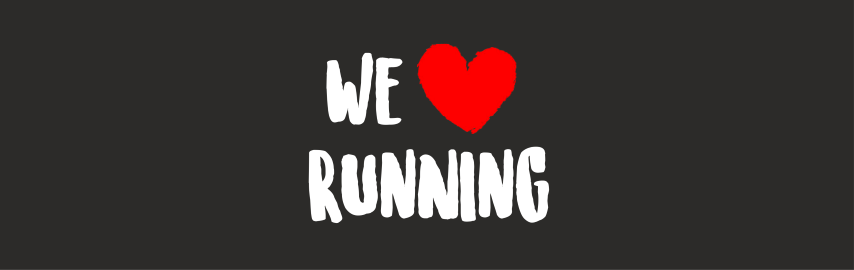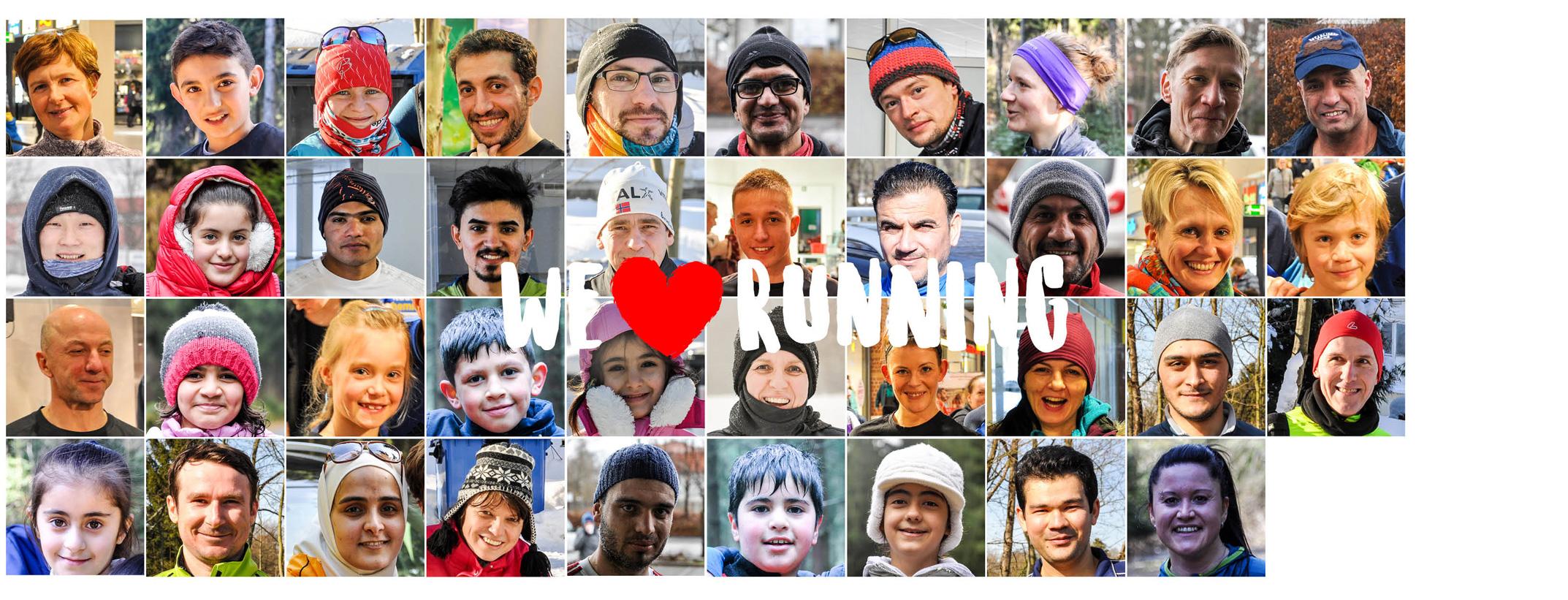
Welche Schrift bzw. was passt dazu?
Ob die aber jetzt schon das Non-Plus-Ultra ist, weiß ich nicht
Muss es noch nicht sein :-)  Ich ändere es ab, verwende es einfach so und dann kann ich für die nächste Einsätze immer noch optimieren.
Und probier mal einen N-Wechsel
Wie macht man das?
Wie ich es oben im Screenshot erklärt habe: einfach Groß- und Kleinbuchstaben abwechseln:
RUnNInG
Meiner Wahrnehmung nach bisher die beste Lösung, besonders, weil das Herz nicht mehr als Verb gelesen werden muss, was ja nicht immer gut ersichtlich war.
Das "angerissene" Herz passt nun deutlich besser zur Schrift und ins Bild. Ich würde aber die Farbe wieder auf ein dunkleres rot ändern (wie vorher) und den rechten Porträt-Block etwas nach rechts schieben.
Ich würde aber die Farbe wieder auf ein dunkleres rot ändern
Ich würde das laufende Paar nicht im Herzen platzieren. Insgesamt klemmt das für meinen Geschmack alles etwas. Versuch mal den Elementen ein wenig Luft zum Atmen zu geben.
edit: ja oder so, wenn der Text mit drin steht ist es besser. Luft würde ich trotzdem reinlassen.
Folgende Variante willst Du also nicht nochmal probieren?
WE ❤️
RUNNING
Folgende Variante willst Du also nicht nochmal probieren?
WE ❤️
RUNNING
Doch, will ich auch noch ....
Da ist das Herz jetzt so groß, dass ich es nicht mehr als Teil von »We love running« lesen, sondern als eigenständige Illustration sehen würde.
Für die WE ❤️ RUNNING Variante würde ich das mal ausprobieren (natürlich noch mit dem Hintergrundbild):
Edit: Das Herz fungiert quasi als i-Punkt :-).
Die Portraits würde ich daneben positionieren wie in den anderen Beispielen, jedoch nicht so stark in den Zwischenraum von WE, ❤️ und RUNNING hereinragen lassen.
Und warum muss das überhaupt zweizeilig sein? Oben in 2, 3 Reihen die Fotos und darunter in einer Zeile WE ❤️ RUNNING mit Herz etwa in derselben Schrifthöhe wie der Text. Das vermeidet die ganzen Dimensionierungsprobleme, oder?
:tuschel: Dieses Original der New Yorker Tourismusbehörde war auch einzeilig.
Find' ich gut – der Wald wartet geradezu errannt™ zu werden :nicken::-P
und die Porträts dann lieber ohne Wald ...
1. Ich würde den Slogan mit einem Schatten hinterlegen, damit er besser zu lesen ist.
2. Oder die Portraits um den Text herum platzieren bzw. die Bilder, die der Text überdeckt weglassen (und eins davon unten rechts platzieren in der weißen Fläche).
3. Das sieht ansonsten schon ziemlich gut aus :-).
Edit: Im Bild ohne die Portraits würde ich den Slogan sowohl horizontal als auch vertikal zentrieren.
In einem Slider auf einer Website würden sich die beiden Banner bestimmt gut machen!
Und wenn du die Portraits gleich ganz weglässt? Momentan kann man den Text überhaupt nicht erkennen …
Find' ich gut – der Wald wartet geradezu errannt™ zu werden
Ich bin gegenteiliger Ansicht. Wald, Portraits, Herz und Text – das war an sich okay, hätte aber noch überarbeitet werden müssen. Nur Portraits, Herz und Text – das ist prinzipiell auch okay. Nur Herz und Text – ist ebenfalls okay. Aber Wald, Herz und Text – das geht gar nicht. Angenommen, du willst Werbung für den Autoverkehr machen, dann nimmst du dir doch auch kein Foto von einem nicht befahrenen Autobahnkreuz und schreibst da rein »We ♥ car driving«. Abgesehen davon ist das abgebildete Waldstück zwar idyllisch, aber darin kann man gerade mal langsam gehen, aber ganz sicher nicht rennen. Stört nicht weiter, wenn die Portraits eingearbeitet sind, aber ohne Portraits fällt das doch sofort auf.
Im Bild ohne die Portraits würde ich den Slogan sowohl horizontal als auch vertikal zentrieren.
Bei uns spielt immer das Thema Facebook eine entscheidene Rolle und so muss ich auf die Zeile mit Datum und Veranstaltungsname achten. Deshalb den Slogan etwas weiter oben und nicht zentriert. Vertikal muss er aber in die Mitte, das ändere ich noch ab.
vor 3 Stunden schrieb Designfreak:
und eins davon unten rechts platzieren in der weißen Fläche
auf der rechten Seite fehlt noch ein Zeile mit 4 Bildern, ich war noch nicht ganz fertig :-)
Wegen der besseren Lesbarkeit der Schrift muss ich noch eine Lösung finden. Das passt so noch nicht so toll.
Danke für die Hilfe!
Mit den Fotos lässt sich ein Raster bilden. Wie wäre es denn damit, den Text und das Herz in das Raster einzuarbeiten, also zehn Quadrate (ohne Fotos) im Raster für den Text und das Herz zu nutzen?
Edit 2: Das letzte Bild ist aber besser als das vorherige. Trotz der Symmetrie und der Verteilung des Texts auf fünf Quadrate.
Edit 3: Wenn du jedem Buchstaben und dem Herz ein eigenes Quadrat zuweist, müsste es auch leichter sein, den Text mit der Hand zu schreiben bzw. zu malen. Die Schrift muss dann nicht so wirken, als sei sie quasi in einem Zug geschrieben.
Ich würde die Schrift noch ein wenig nach unten setzen, optisch ausmitteln.